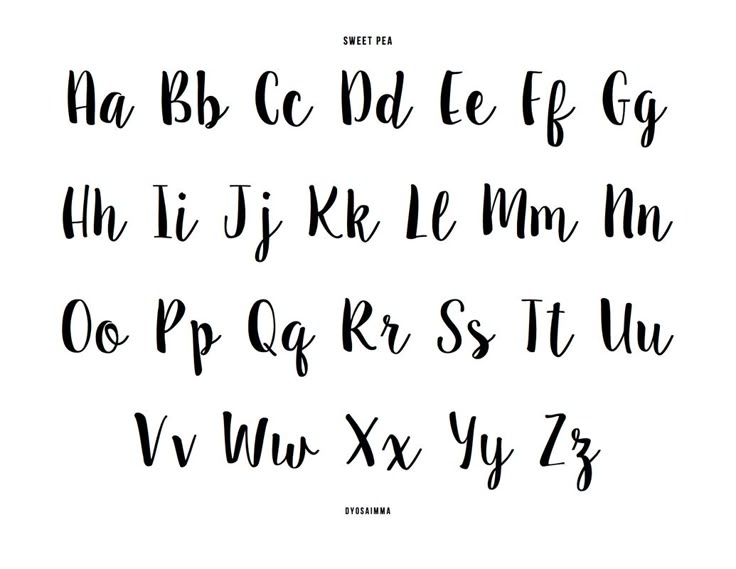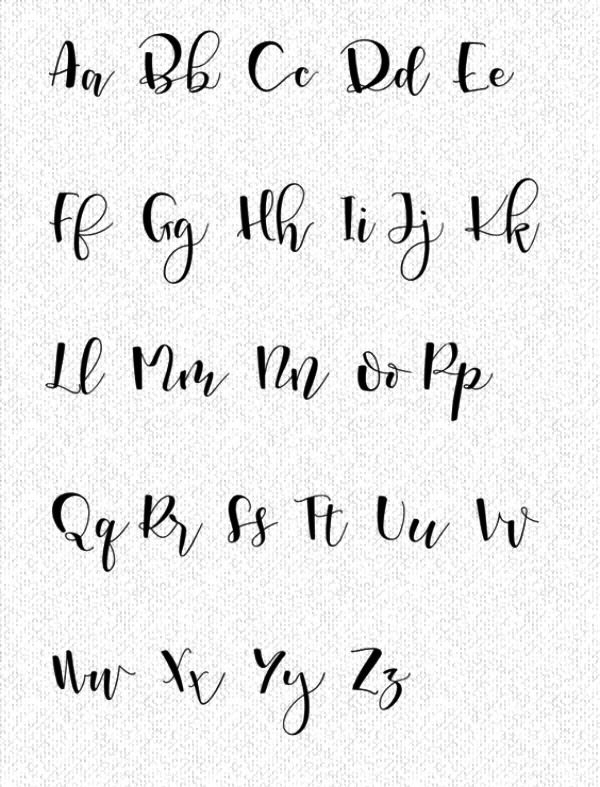
8 известных шрифтов и дизайнеры, которые их создали
Самые известные шрифты в мире встречаются практически везде. Когда вы становитесь дизайнером, все эти засечки и толщина штрихов начинают буквально выскакивать на вас, и вы начинаете узнавать их в окружающей среде. У каждого штриха, который вы видите, есть свой создатель, история и свои фанаты.
Посмотрите, как создавались некоторые из известных шрифтов, и на дизайнеров, которые своими смелыми шагами изменили наш визуальный мир.
Разработан: Максом Мидингером и Эдуардом Хоффманом
Стиль шрифта: без засечек
История создания: Швейцария, 1957 год, шрифтолитейная Haas. Мидингер хотел стать художником, но его отец убедил его, что стоит сфокусироваться на более прикладной профессии. Мидингер взялся за дизайн шрифтов и создал спустя 30 лет вместе с Хоффманом Гельветику. Он предназначался для того, чтобы заполнить отсутствие нейтрального шрифта, подходящего для вывесок.
Где вы могли его видеть: Считается самым распространенным шрифтом в мире. Фильм «Гельветика». Брендинг American Apparel. Логотип Crate & Barrel. Логотип Lufthansa. Логотип Jeep. Система вывесок Нью Йоркского метро. И многое другое.
Разработан: Джамбаттиста Бодони
Стиль шрифта: с засечками
История создания: Италия, 1798. Бодони был нанят в качестве официального наборщика текстов для ряда итальянских герцогов. Эти герцоги были влюблены в его работу и предложили ему работу за печатным станком во дворце в Парме. В свое время его называли «дизайнер королей и король дизайнеров». После его смерти, его работы объединили и создали шрифт, который мы сейчас знаем как «Бодони».
Где вы могли его видеть: Один из самых старых шрифтов, который используется по сей день. Журнал Vogue. Постеры к мюзиклу «Mamma Mia!». Логотип Nirvana. Товарный знак Columbia Records.
Разработан: Виктором Лардентом
Стиль шрифта: с засечками
История создания: Англия, 1931.
Был разработан по заказу британской газеты The Times после того, как шрифт дизайнера Стэнли Морисона подвергся критике из-за плохой читаемости. Морисон помогал штатному дизайнеру создавать Times New Roman, который затем разошелся по всему миру.
Где вы могли его видеть: Ваш доклад из университета. Набранный с двойным пробелом. 12 шрифтом. Обычно его называют «шрифт наименьшего сопротивления». Включен во все версии Microsoft с 1992 года. Часто используется в книгах и газетах. Его высокая разборчивость отлично подходит для текстов. Ни один список шрифтов не может быть полным без него.
Разработан: Паулем Реннером
Стиль шрифта: геометрический гротеск
История создания: Франкфурт, 1927 на шрифтолитейной фабрике Bauer (Bauer Type Foundry). Футуру часто ошибочно считают первым геометрическим шрифтом без засечек. Однако, эта почесть принадлежит шрифту Erbar из шрифтолитейной Ludwig & Mayer.
Futura была создана из-за популярности в то время таких шрифтов. Но в связи с тем, что Bauer была гораздо больше, чем Ludwig & Mayer, Футуре удалось пройти испытание временем.
Где вы могли его видеть: Огромное количество постеров к фильмам, включая «Гравитацию», «Красоту по-американски», «Исчезнувшую» и «Интрестеллар», а также сериалы, такие как «Остаться в живых» и «Улица Сезам». Используется в высоко оцененном графическом романе «Хранители» (Watchmen). Это любимый шрифт известных режиссеров Уэса Андерсона и Стэнли Кубрика, поэтому его часто можно наблюдать в их фильмах.
Разработан: Адрианом Фрутигером
Стиль шрифта: без засечек
История создания: 1974. Фрутигер, швейцарский дизайнер, был нанят американской шрифтолитейной фабрикой Mergenthaler. Компания хотела печатную версию шрифта Roissy, которую Фрутигер создал для вывесок нового аэропорта «Шарль де Голль» в Париже. Фрутигер полагал, что у шрифта была ясность и «нагота» из-за отсутствия дополнительных функций.
Где вы могли его видеть: Официальный шрифт многих университетов и колледжей, в том числе колледжа Клермонт Маккена (Claremont McKenna College), Корнелльского университета (Cornell University) и Университета Южной Калифорнии (the University of Southern California). На вывесках систем скоростных электропоездов (BART), железнодорожной компании Amtrak и Сиднейской CityRail. Наиболее заметным можно считать использование этого шрифта на официальных банкнотах евро Европейского союза.
Разработан: Клодом Гарамоном
Стиль шрифта: антиква старого стиля
История создания: Один из самых старых шрифтов, который используется до сих пор. Датой возникновения считается примерно 1530 г. Время политических и социальных беспорядков во Франции. Это была эпоха, которой были необходимы новые шрифты, чтобы сформулировать новые идеи. Позже, после смерти Гарамона, шрифт был приобретен французско-немецкой шрифтолитейной компанией, и начал использоваться как шрифт в 20-м веке.
Где вы могли его видеть: В основном используется для печати. До сих пор один из самых популярных шрифтов во французском книгоиздании. Логотип Abercrombie & Fitch. Якобы считалось, что этот шрифт мог сохранить США $ 400 млн. из-за его более тонких штрихов (предупреждение: это был просчет).
6.
Рукописные шрифты
Рукописные шрифты отличаются от рукописных тем, что они используют более естественный стиль письма. Существует множество стилей почерка, поэтому этот шрифт может быть очень широким.